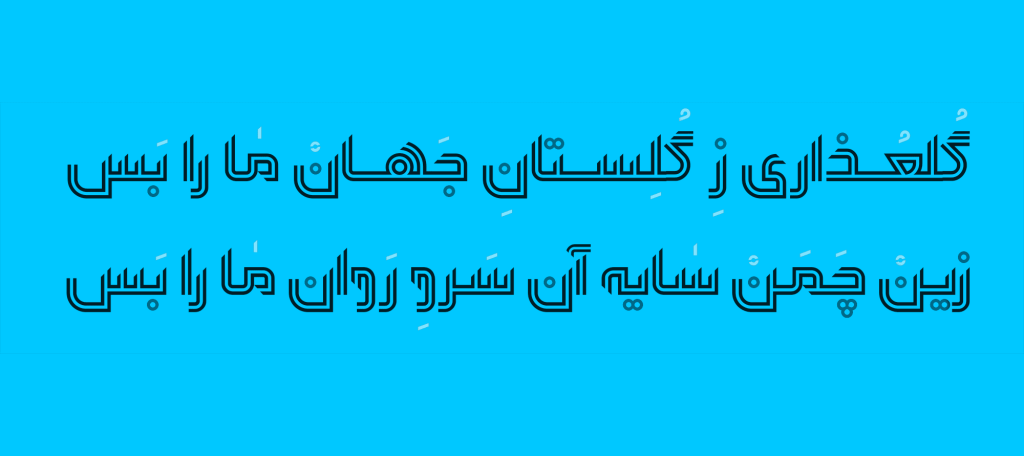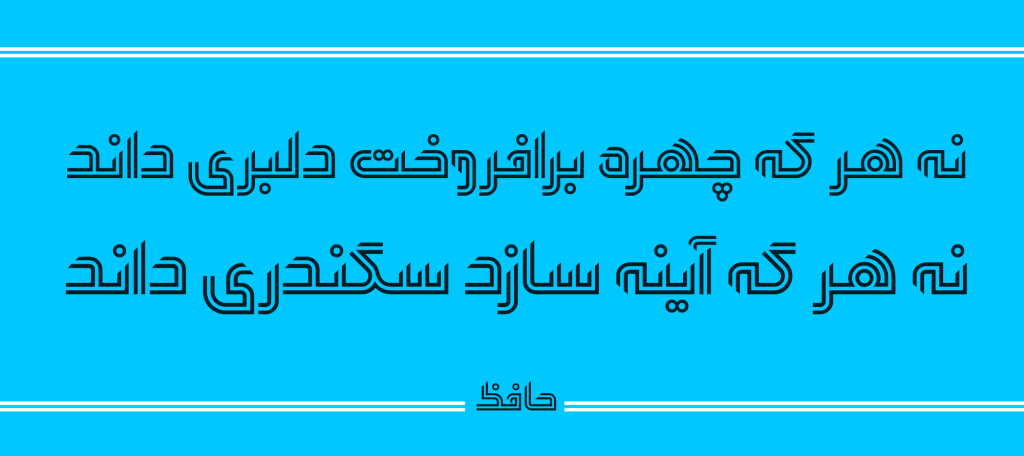
فونت ارژن
فونت ارژن ساخته و طراحی شده توسط آقای مصطفی اوجی از اولین طراحان تایپ فیس در ایران می باشد. وی این حرفه را به صورت آکادمیک در رشته هنر از دانشگاه تهران آموخته و دنبال نموده است. همانطور که در بالا اشاره شد این تایپ فیس به سبب ویژگی نمایشی و ظاهر تزئینی که دارد مناسب متون کوتاه و عناوین و تیتر های تبلیغاتی و مطبوعاتی است چرا که به واسطه همین ویژگی مذکور در کوتاه ترین زمان به دنبال جذب نگاه خوانندگان و مخاطبین به خود است.
ارژن قلمی هندسی با ویژگی نمایشی
با دقت در فرم های طراحی این قلم که از خانواده هندسی تبعیت می کند می توان دریافت که از دسته تایپ فیس های منولاین می باشدو ساختار و اسکلت آن از ساخته شده از خطوط صاف و دوایر هندسی تشکیل شده است. فونت دلنیا در ویژگی های ذکر شده فصل مشترک و قرابت معنایی نزدیکی با این تایپ فیس دارد. با این تفاوت که انرژی و رهایی بیشتری نسبت به این قلم دارد.
ارژن الهام گرفته و اقتباسی از خط کوفی معلقی که یکی از قلم های قدیمی با هویت ایرانی است می باشد. این تایپ فیس دارای شخصیتی جدی و جسور است که در عین حال از نشاط و شادابی خاصی هم بهره مند است. در زیر تصاویری از این تایپ فیس خاص برای شما عزیزان قرار داده شده است.